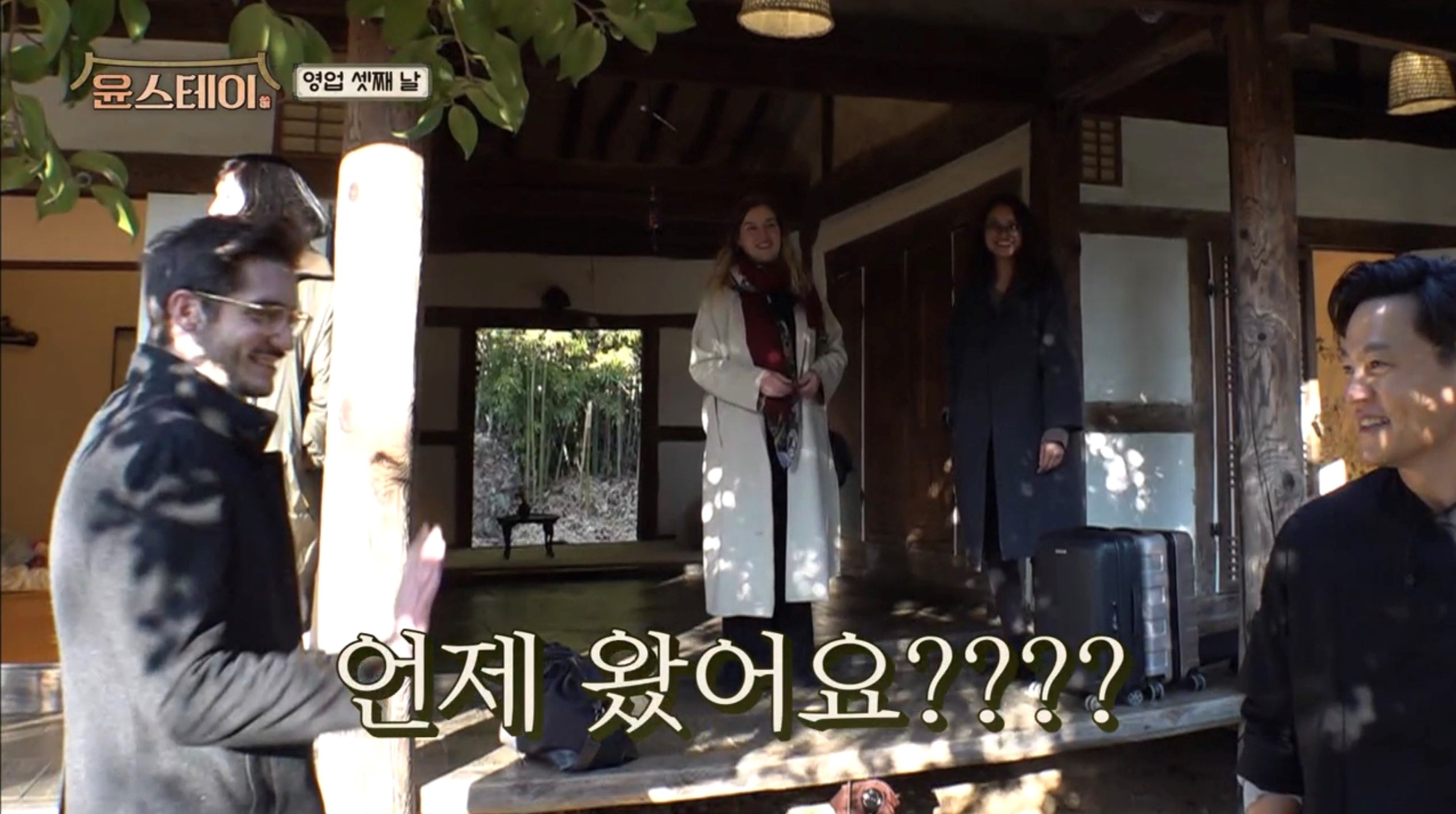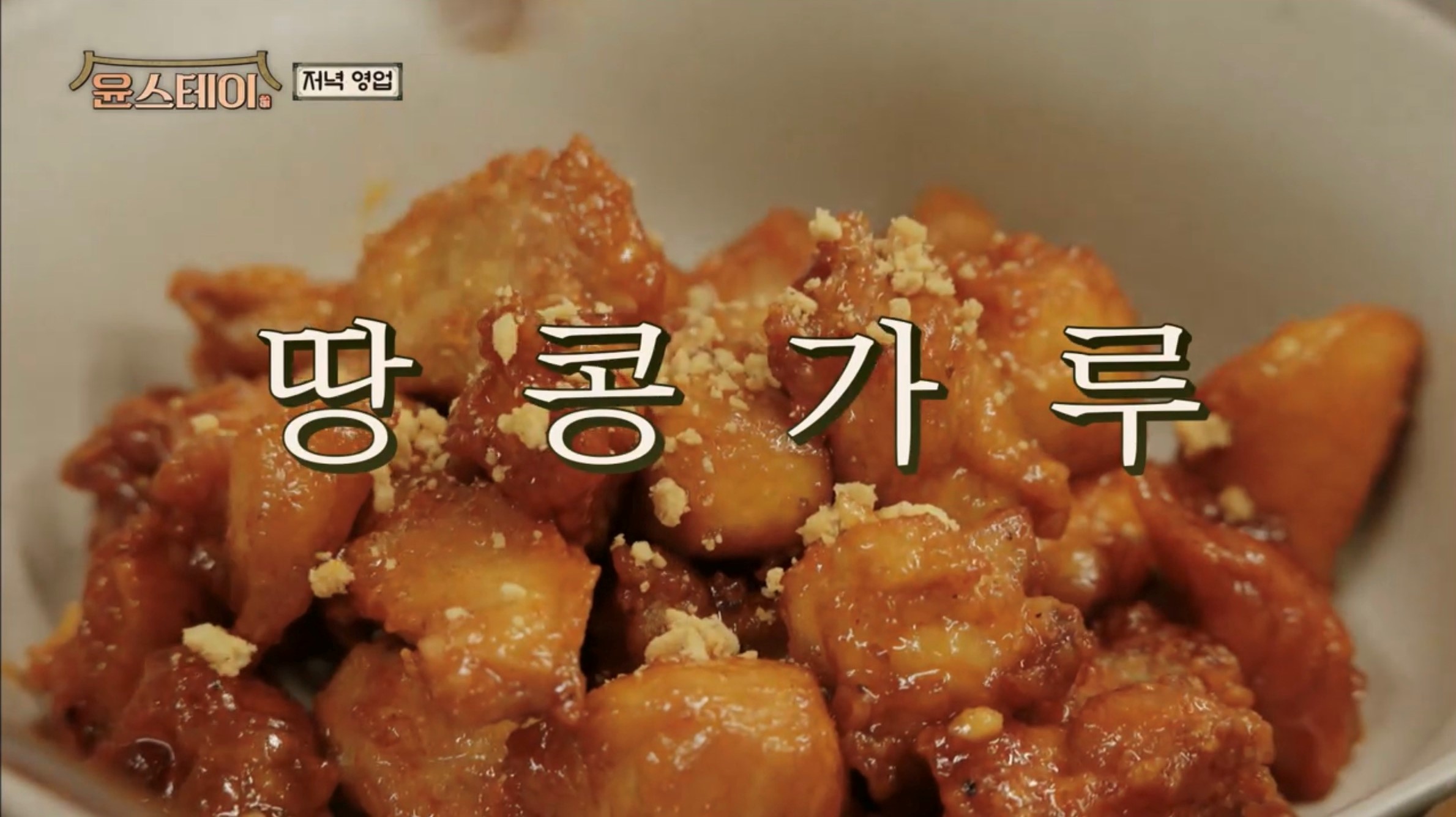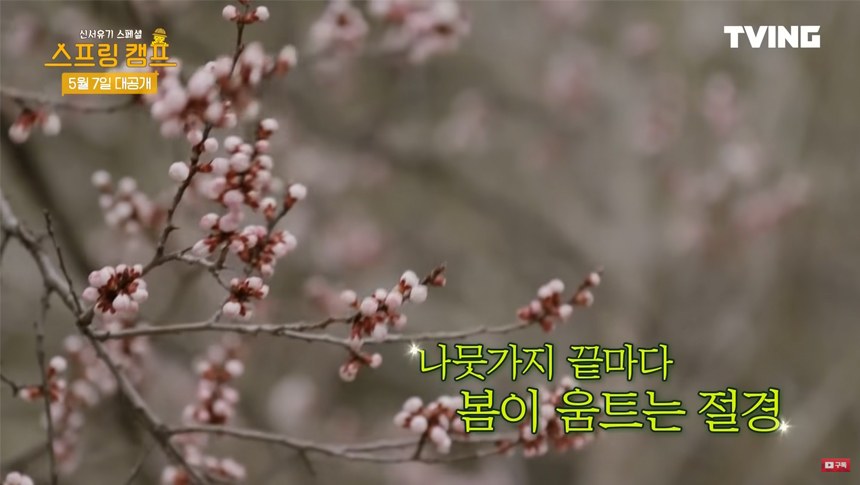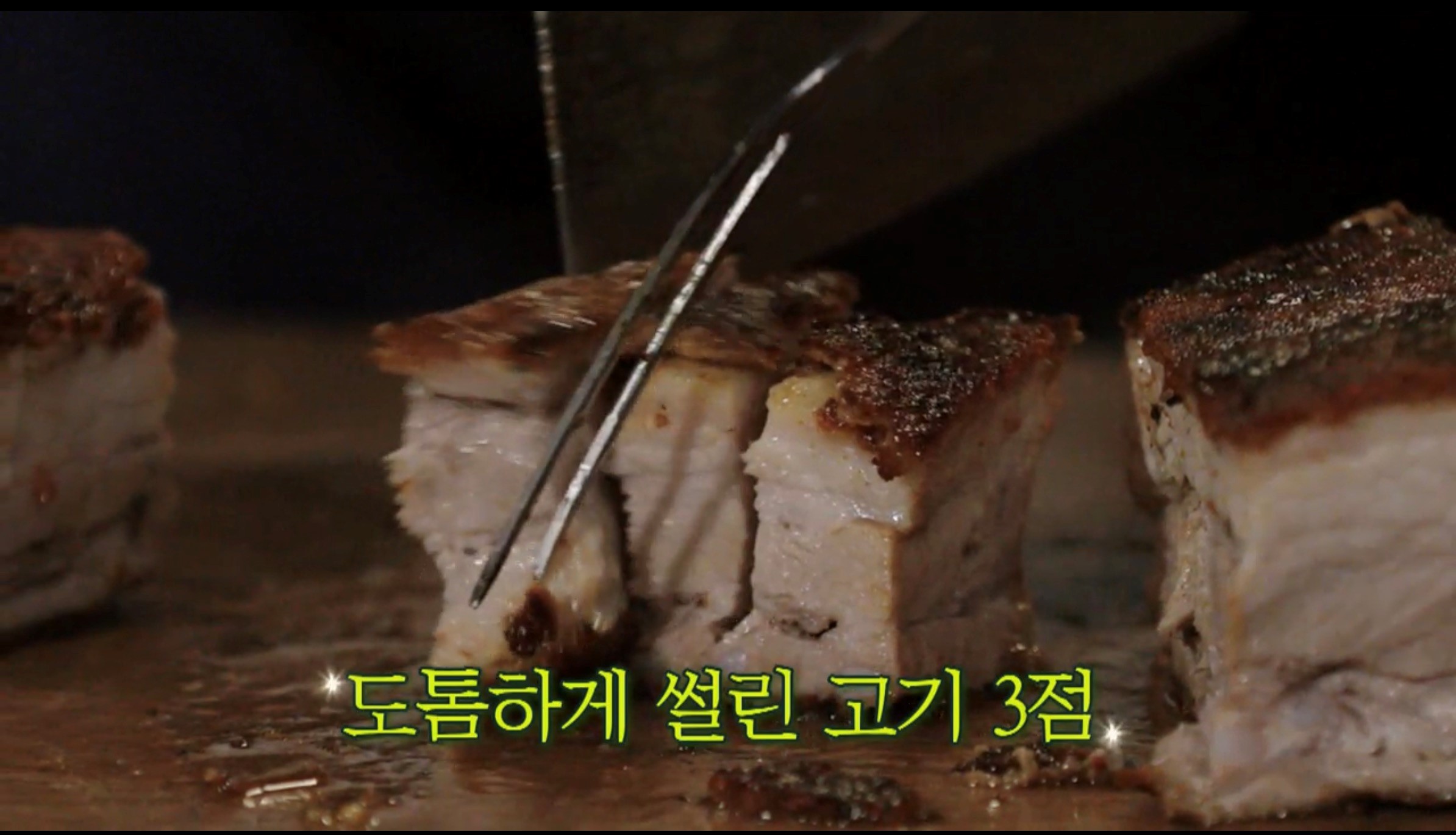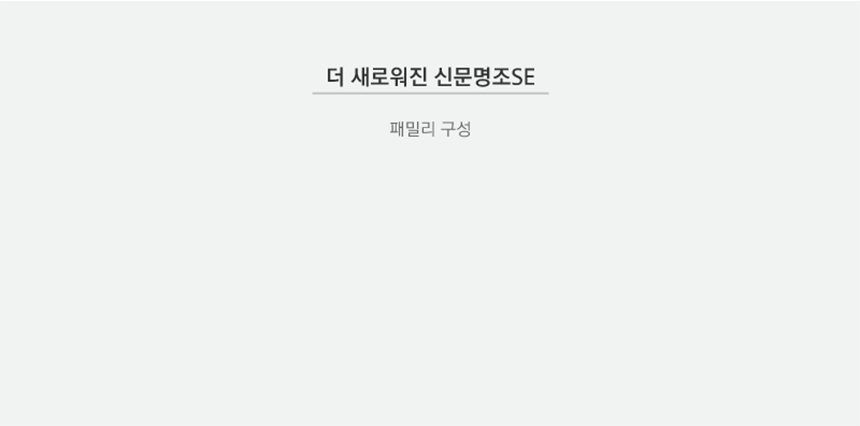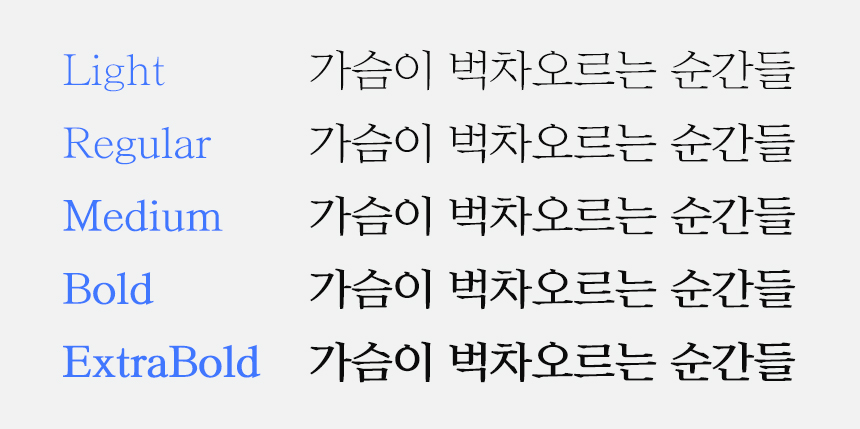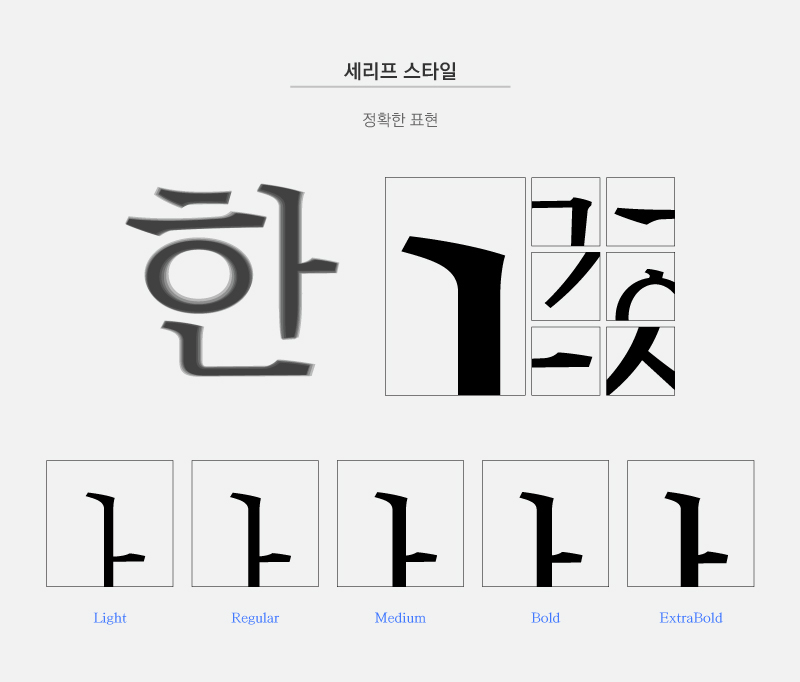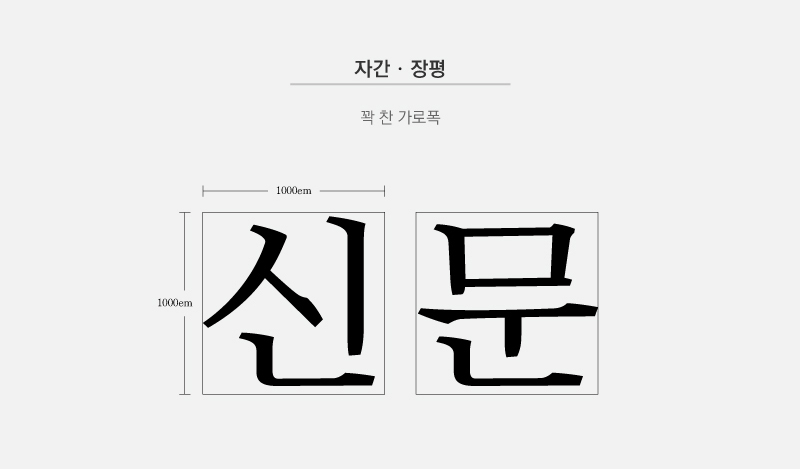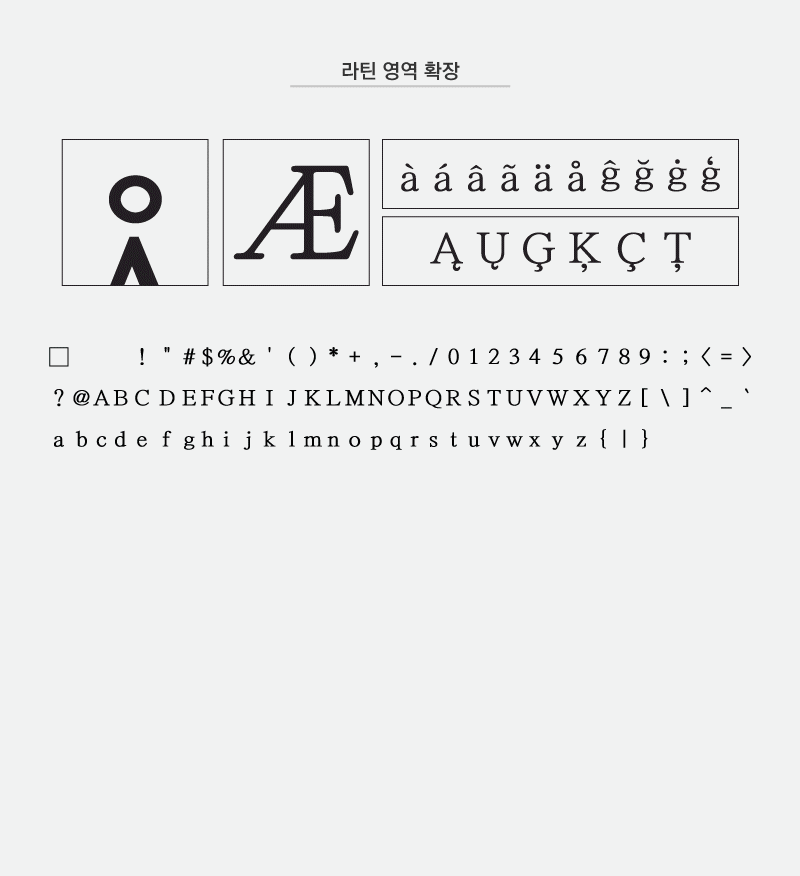
오늘은 새롭게 리뉴얼된 8월의 신서체를 소개해 드려요! 기존의 'Rix신문명조' 서체의 디자인과 가독성은 그대로, 웨이트를 추가해 사용성을 높인 「Rix신문명조SE(Special Edition)」폰트입니다. 업그레이드된 SE 버전 신문명조는 더 세분화된 5종 웨이트와 라틴문자 영역 확장이 제공됩니다. 새로운 제목용, 자막용 명조의 기준이 될 서체를 한 번 만나볼까요?
자막의 새로운 패러다임
요즘 방송을 보면 정말 다양한 폰트들이 사용되는 것을 볼 수 있습니다. 컷이 바뀔 때마다 다른 폰트가 나오기도 합니다. 양질의 콘텐츠가 쉴 틈 없이 쏟아지고 있는 지금 자막의 활용이나 의존도도 더욱 높아지고 있으며, 여러 가지 감정과 상황을 표현하는 자막으로 다양한 디자인의 서체들이 쓰이고 있습니다.
특정 폰트들은 어떠한 분위기나 감정을 드러내기도 하는데요. 그중 명조체는 때론 위트 있는, 때론 감성적인 분위기를 연출하는 매력을 갖고 있습니다. 특히나 평이 넓고 여유로운 감성을 가진 Rix신문명조 서체는 안정적인 형태와 특징적인 디자인 덕분에 인기 방송들에서 활용된 것을 쉽게 찾아볼 수 있습니다.
기존 신문명조 서체는 특히 예능 프로그램에서 많은 활약(?) 중인데요. 재밌는 상황이나 감정을 표현할 때, 아름다운 풍경이나 분위기를 묘사할 때, 음식이나 요리를 하는 장면 등 다양하게 사용되고 있습니다. 가로폭이 넓은 명조체가 흔하지 않고, 또 재치 있는 표현과 감성적인 연출 모두 아우를 수 있다는 점이 메리트가 있습니다.
높아진 활용도의 5종 웨이트
3종 웨이트를 갖고 있던 신문명조 서체가 방송 자막이나 타이틀로 자주 사용되는 점을 고려하여 Bold와 ExtraBold 2종을 추가로 파생했어요. 다양한 분야에서의 쓰임이 점점 높아지는 만큼 그에 맞는 추가 제작을 진행했습니다.
완성도를 높이는 디테일
디테일이 살아있는 각이 진 세리프는 서체의 완성도를 더욱 높여줍니다. 정확하고 세밀한 각과 유려하게 흐르는 곡선이 아름다운 조화를 이루는 세리프 디자인입니다.
꽉 찬 넓은 가로폭과 적절한 자간 설정을 유지하여 여유롭고 시원한 인상을 줍니다. 일정한 글줄로 가독성이 높고, 편안함을 느낄 수 있는 안정적인 구조입니다.
자유롭고 폭넓은 사용성
Rix신문명조SE 폰트에서는 라틴문자 영역을 확장했습니다. 더 다양하고 자유로운 표현이 가능해져 여러 분야에서 사용성이 높아질 것으로 기대됩니다.
💡 Rix신문명조SE 사용 예시 💡
방송 프로그램, 광고, 유튜브 등 영상 타이틀이나 자막으로의 활용도가 높은 서체입니다. 굵기를 조정하여 사용하면 한 영상이나 이미지 내에서 통일성 있으면서도 풍부한 표현을 할 수 있습니다.
여유로운 공간감과 높은 가독성을 가진 폰트의 특징에 따라 차분한 감성의 패키지나 제품 디자인에도 활용하기 좋습니다. 위와 같이 깨끗하고 깔끔한 이미지를 연출할 수 있습니다.